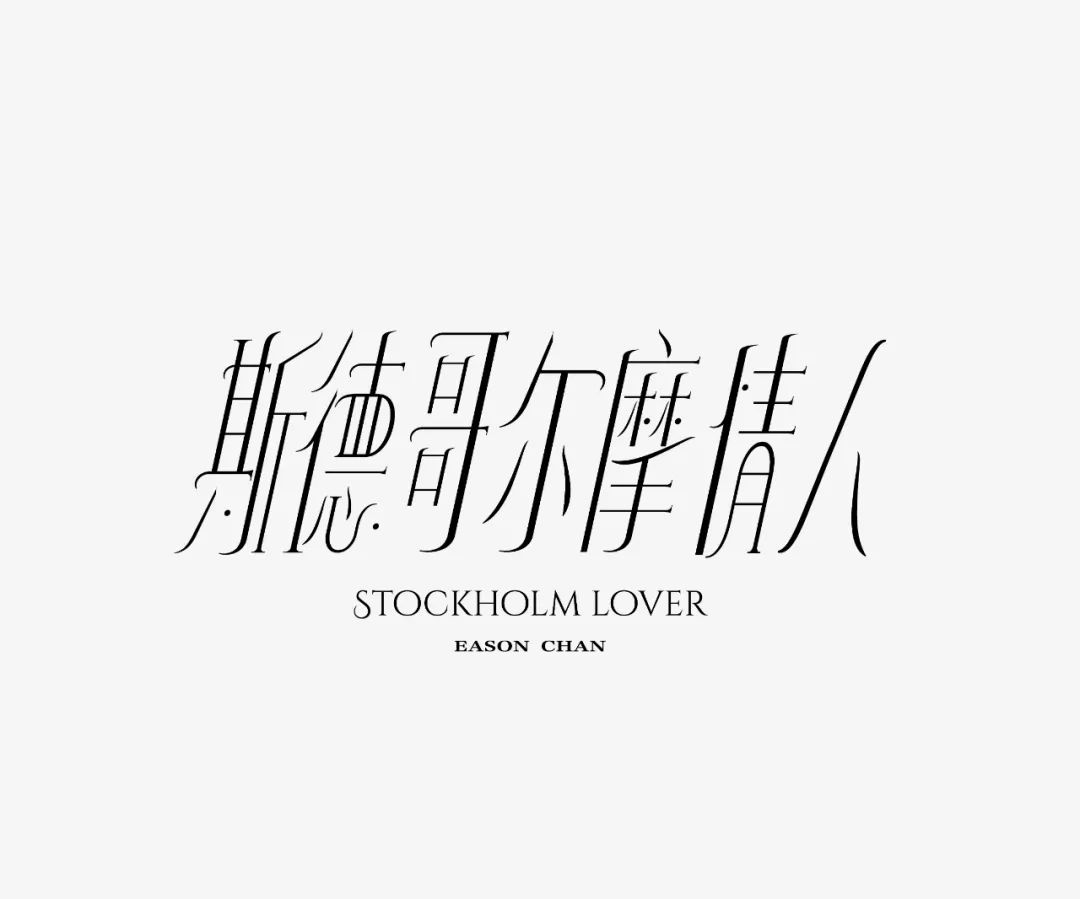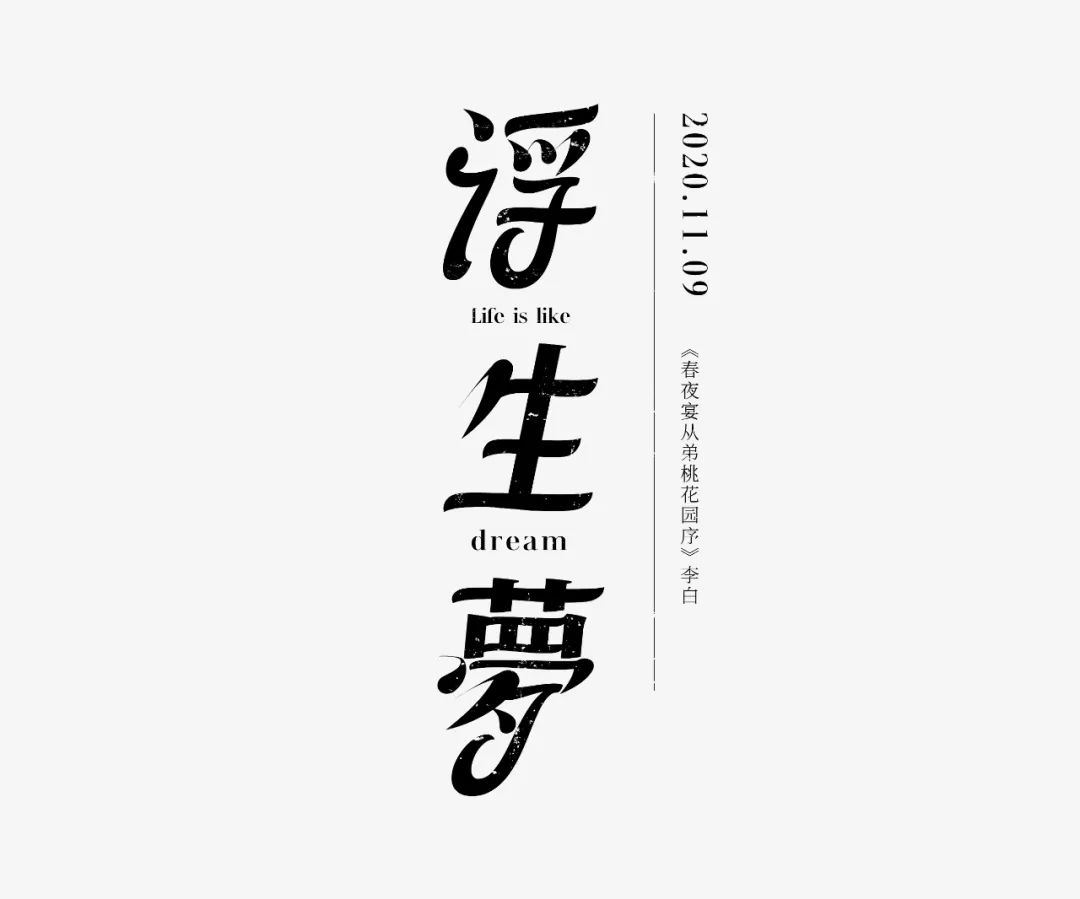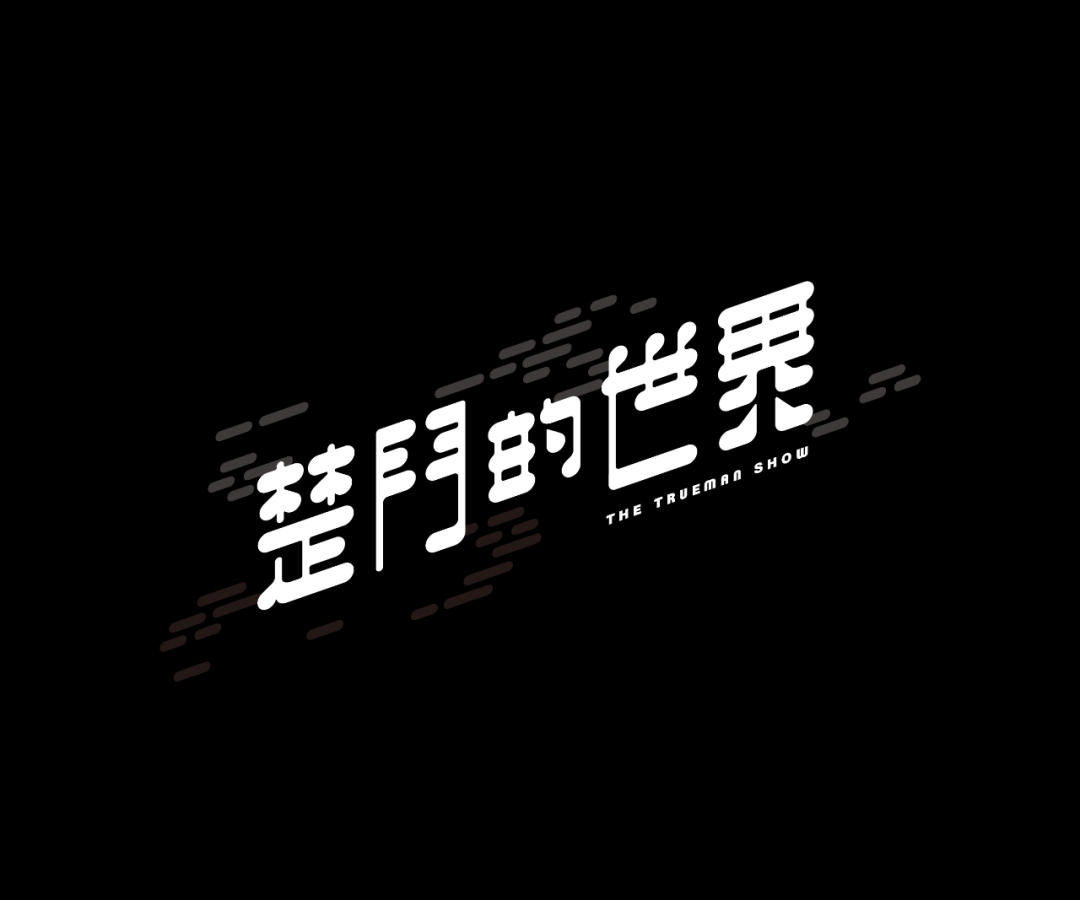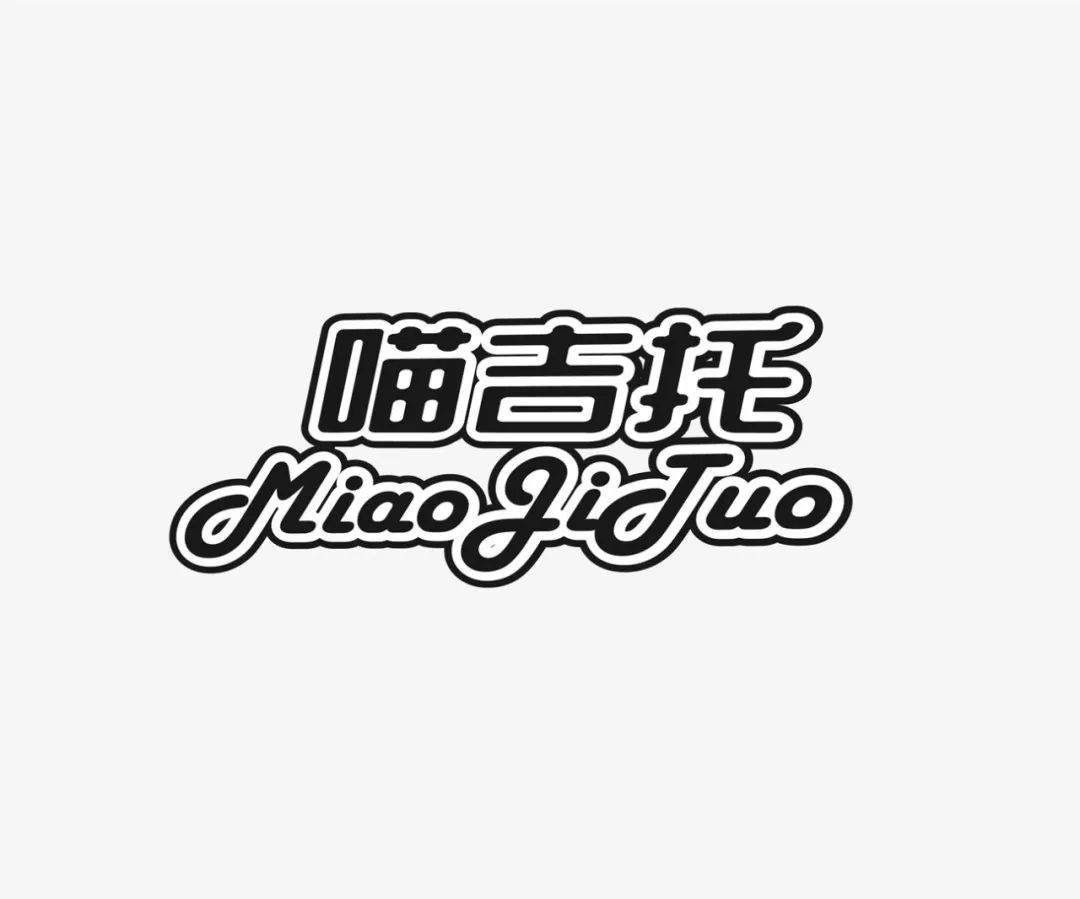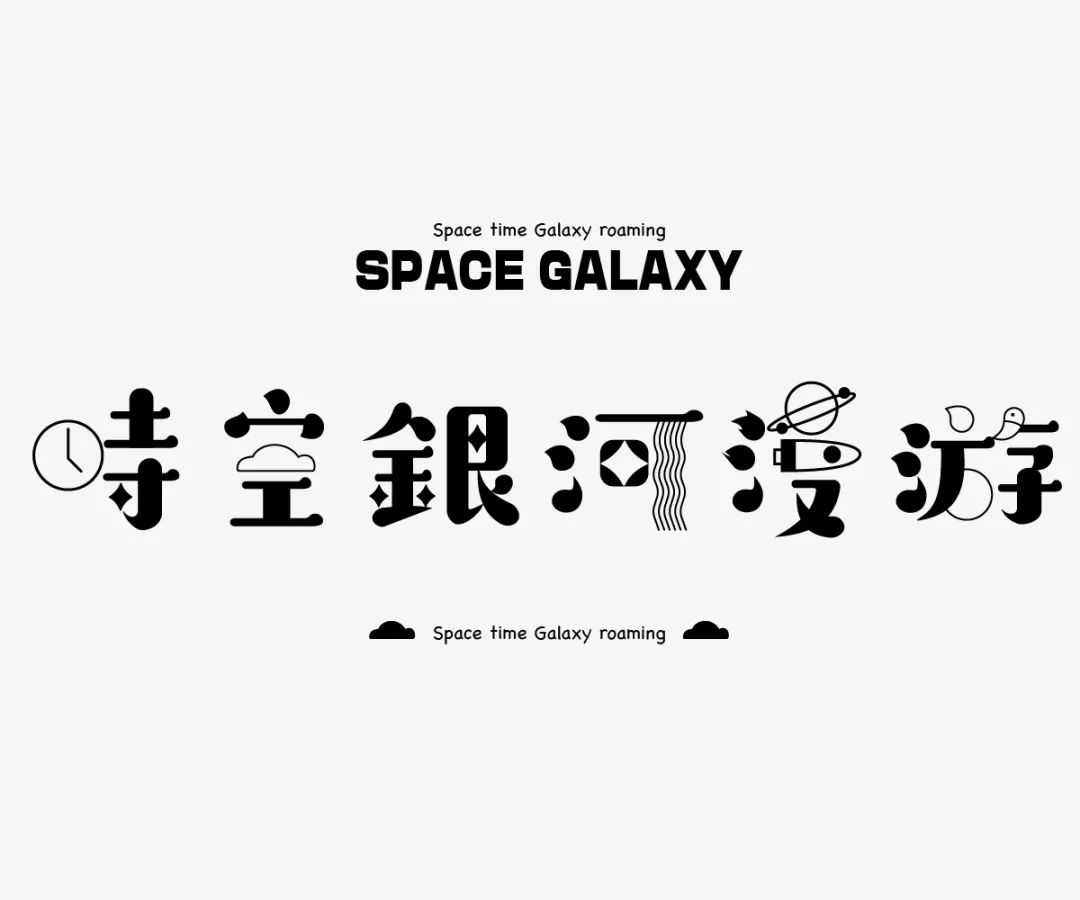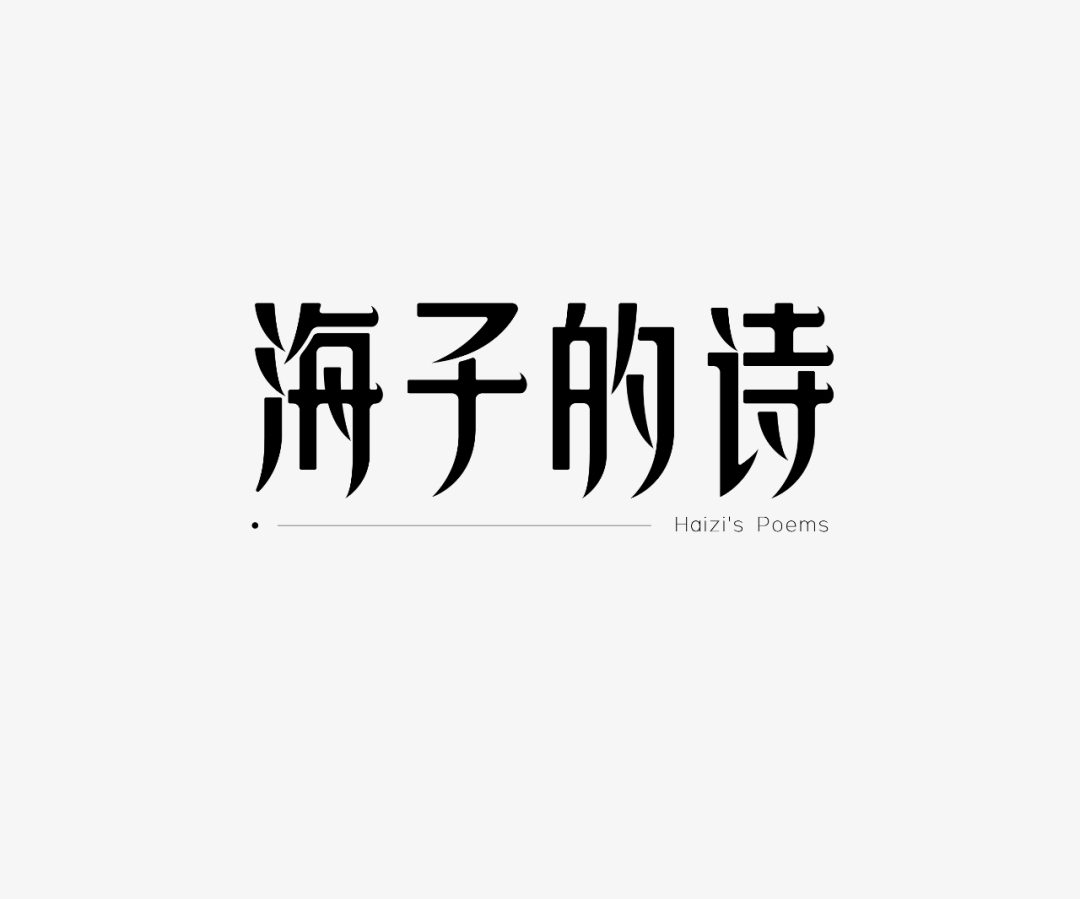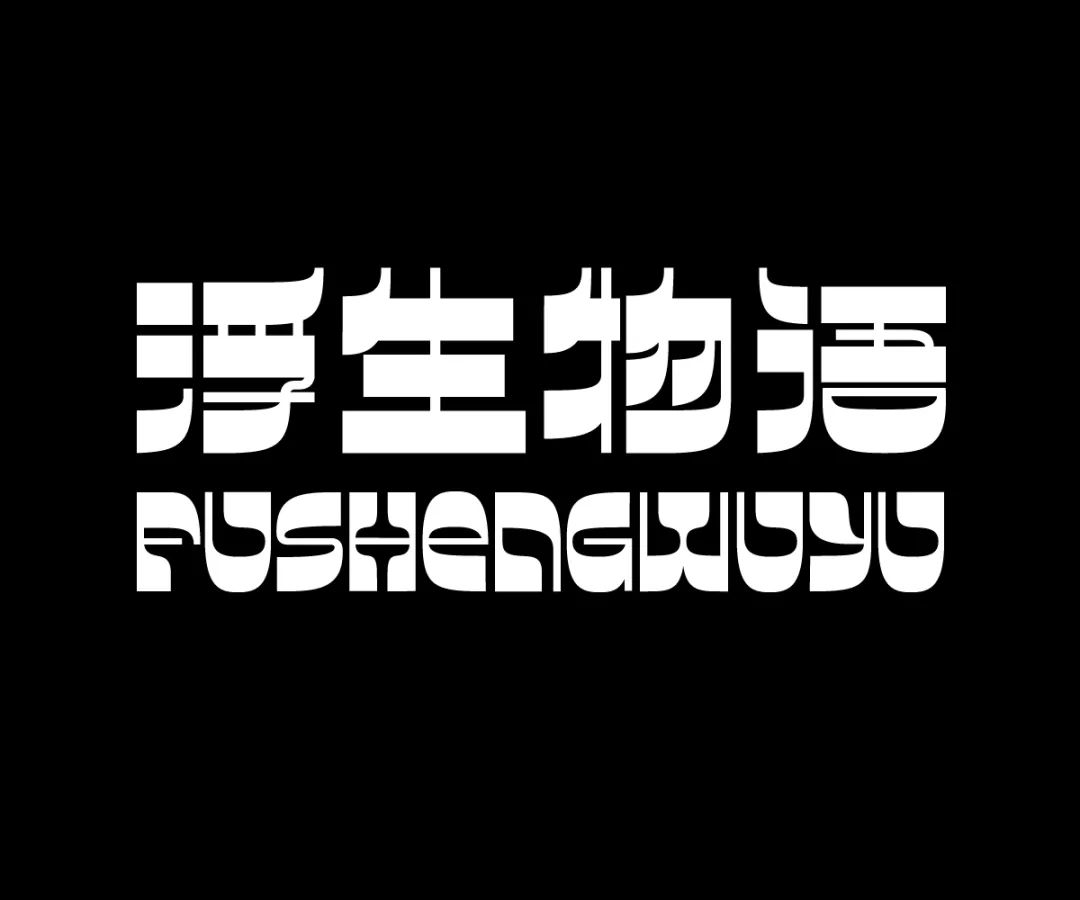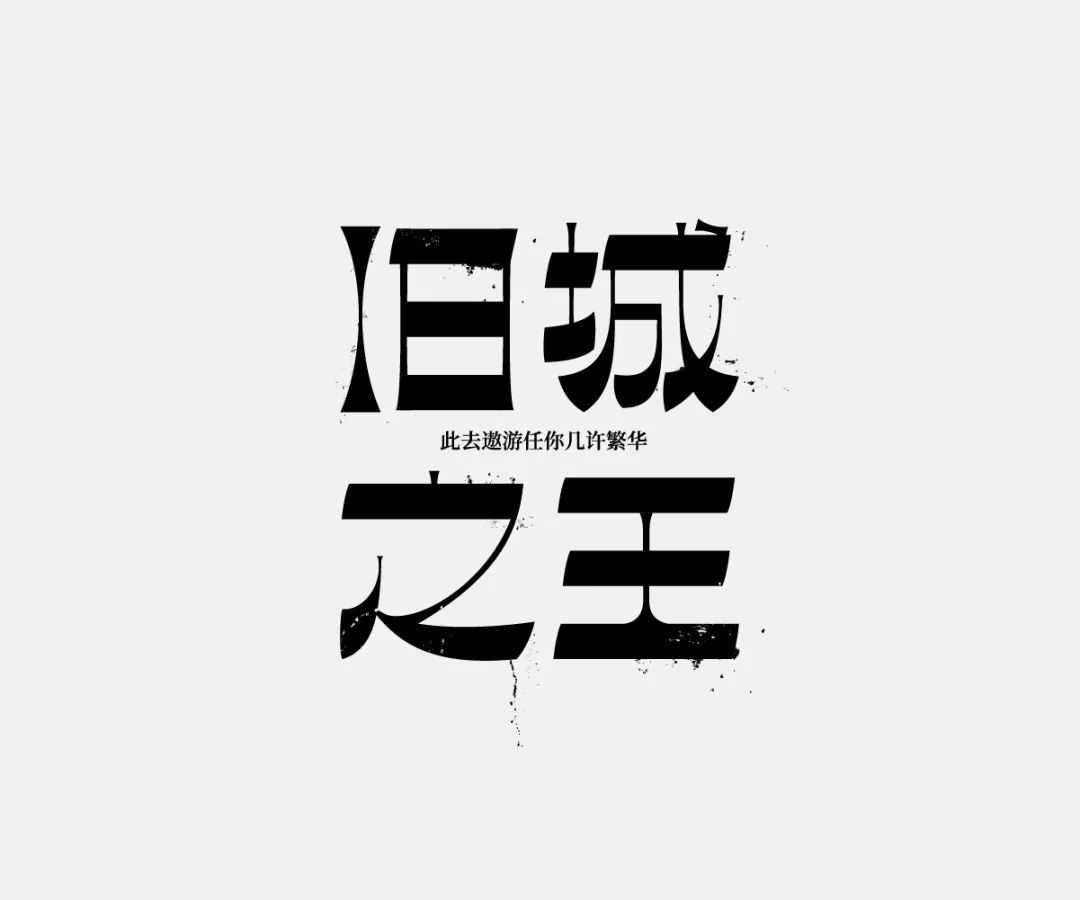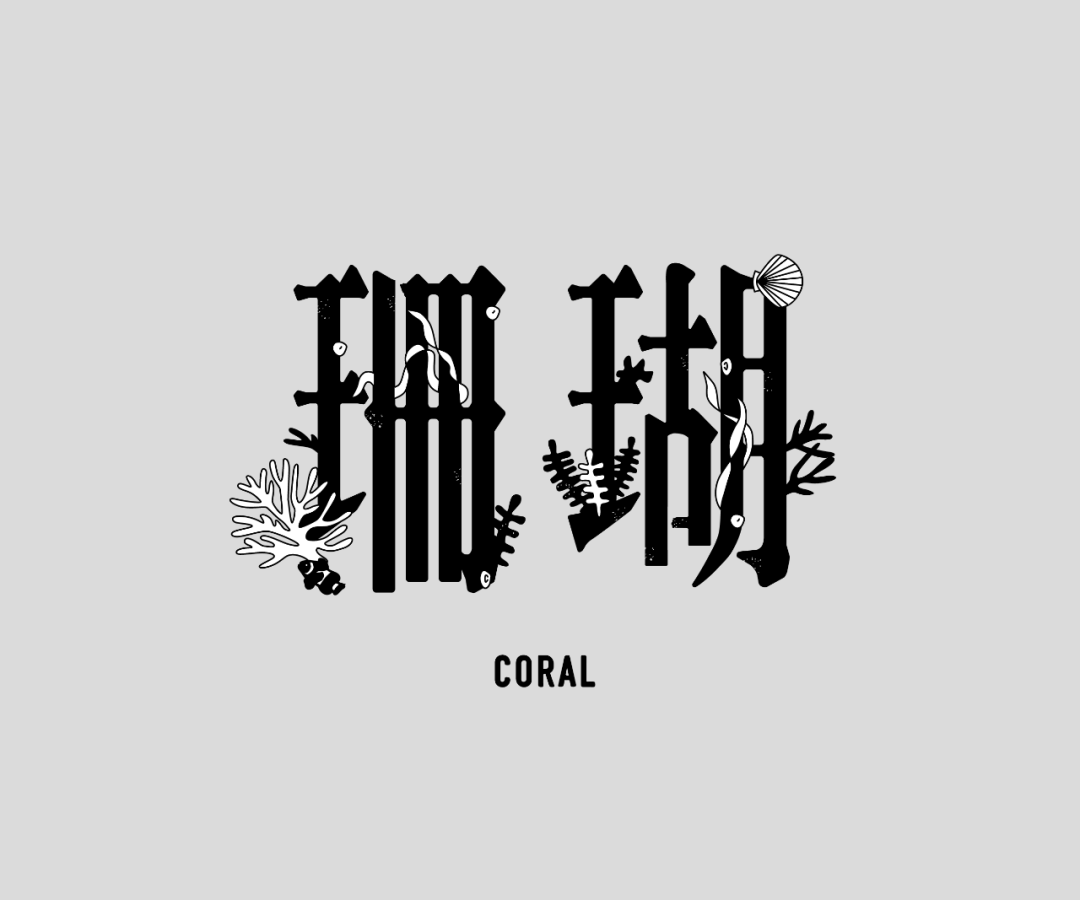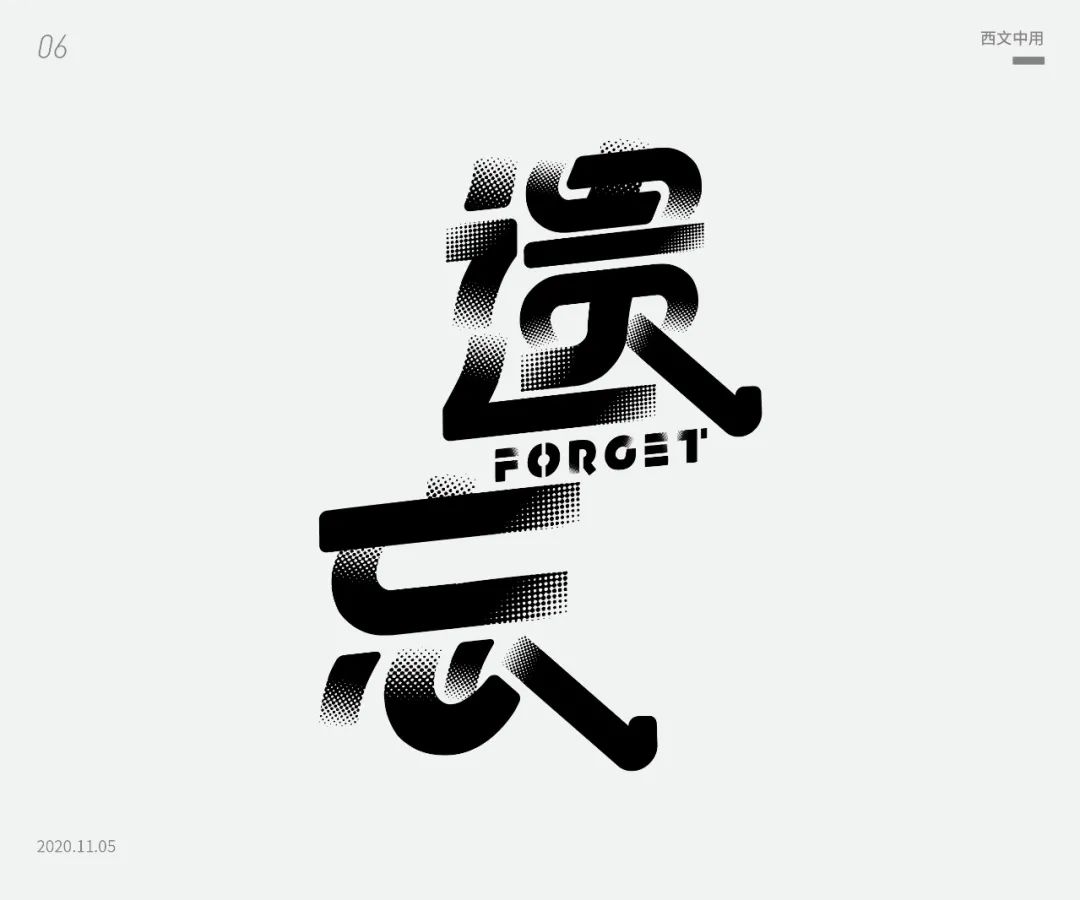
用西文来做中文字体!比较有趣的字体设计方法
作为设计师,在视觉设计工作中,例如运营活动、海报、书籍、包装等,差不多每项任务都会使用到字体,也离不开字体。想要设计一个好字体,有什么样的技巧来提升呢?
在字体设计中,常用技法包括替换法、共用笔划法、卷叶法、断肢法、错落法、尖角法等等,还有一样是:西文中用。
西文中用,就是用西文的字符来代替中文的某个笔画或部首,是一种比较有趣的字体设计方法。
下面,同大家分享一下上期字体课第6节部分同学的西文中用字形作业。主要训练借用古字或是其他国家文字中的某些笔画来进行造字,来看看大家的学习成果。
先看第28期几位同学的。
接下来看看第29期部分同学的。
她们刚刚在12月中旬完成整个课程的学习。
再将其制作成动效的
非常有意思
在设计之前,会通过分析项目需求的风格特征,来确定一款适合此项目风格的西文字体,之后进行拆解利用笔画进行中文造字,从西文中去找类似结构的笔画,最终进行字形的整体调整。
随着字体设计的发展,现在的字体设计和商业场景的结合更加紧密,被应用的更加广泛,越来越受到甲方粑粑的重视。包括近年来很多品牌的Logo设计,字体就得到了高度重视。因为品牌重视信息传播的高效,而字体相对图形可以被更快的识别,所以字体Logo自然成了品牌追捧的设计方向。
字体设计的方法和形式非常多,西文中用只是其中的一种。大家只有不断的尝试,把不同的字体、不同的设计技巧进行组合,才能设计出完美与合适的字体。
希望今天学生字体作业的分享,能给大家带来灵感和启发。